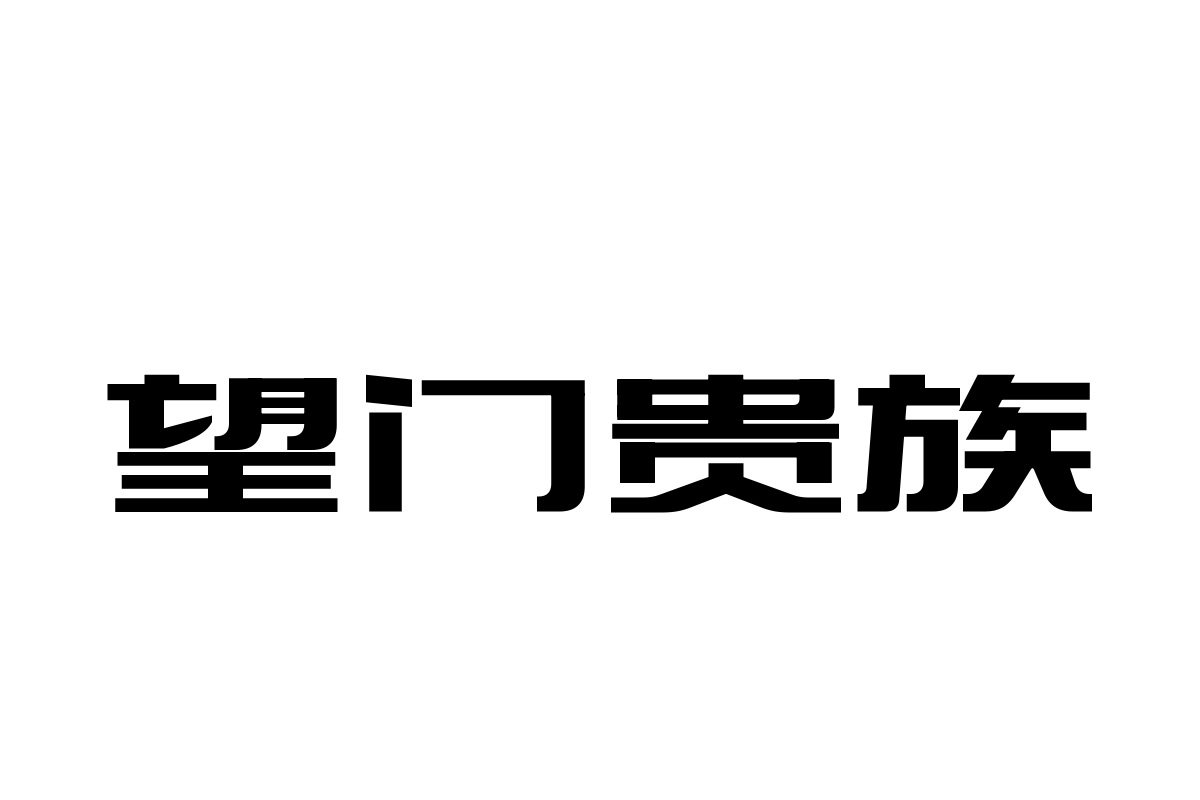
三极刃黑是一款超粗字体,它以其独特的设计风格和强大的可读性而受到广泛欢迎。这款字体的特点是线条粗犷有力,给人一种强烈的视觉冲击力。
在设计上,三极刃黑采用了简洁明了的线条,使得文字看起来更加清晰易读。同时,它的笔画粗细不一,增加了字体的层次感和立体感。这使得三极刃黑在各种场合都能展现出其独特的魅力。
除了美观之外,三极刃黑还具有很高的实用性。由于其线条粗犷有力,因此非常适合用于需要强调重点或表达强烈情感的场合。无论是在广告、海报、标题还是正文中,三极刃黑都能发挥出其独特的优势。
总的来说,三极刃黑是一款非常出色的超粗字体,无论是从设计上还是实用性上都表现出色。如果你正在寻找一款能够提升你的作品视觉效果的字体,那么三极刃黑绝对值得一试。
三极刃黑 超粗